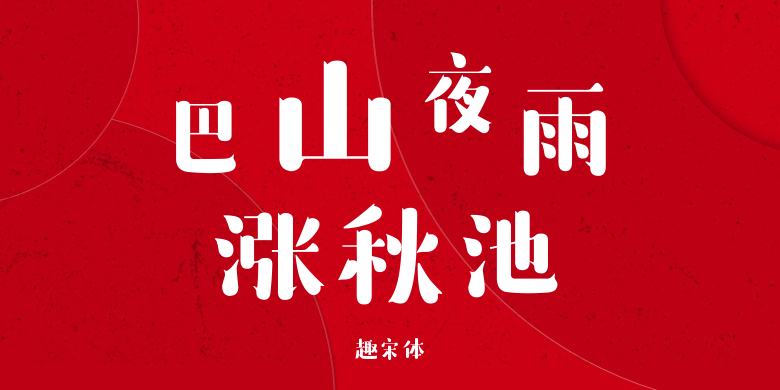
趣宋体
趣宋体,这款字体结构工整、笔画清晰,兼顾美观与易读性,适用于标题、正文、海报、包装、LOGO 等多种场景。字形优雅稳定,风格百搭耐看,适配日常排版与创意设计,让文字呈现更舒适、更具质感。趣宋体一笔一画,皆是细节,以均衡的比例、流畅的线条打造舒适视觉体验,字形端正大气,风格简约现代。无论是商业设计、品牌宣传还是日常排版,都能轻松驾驭,让文字更有格调与力量。趣宋体字体下载。